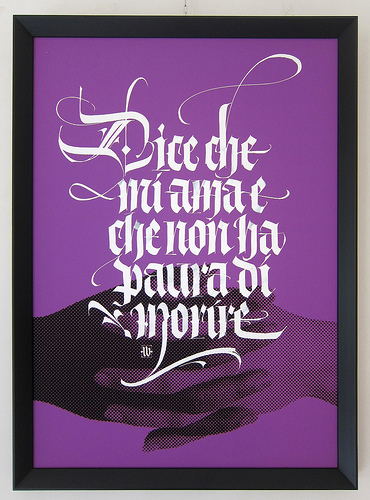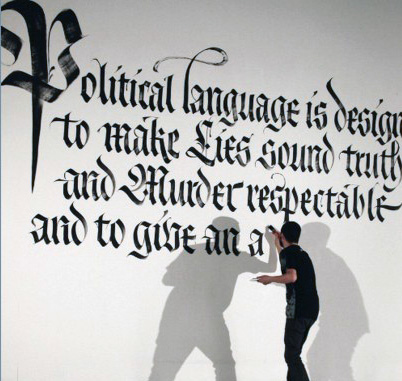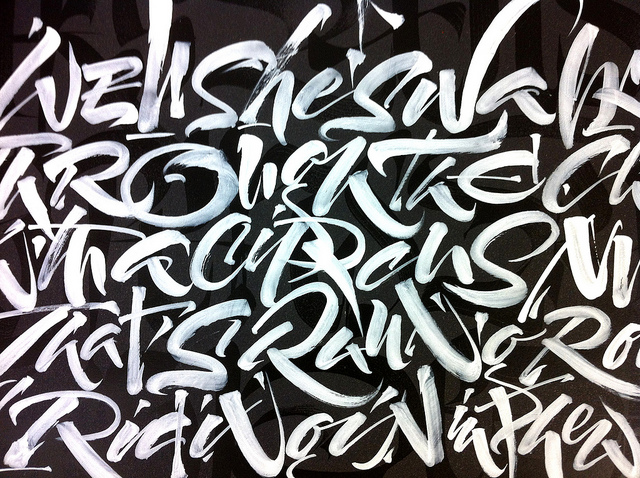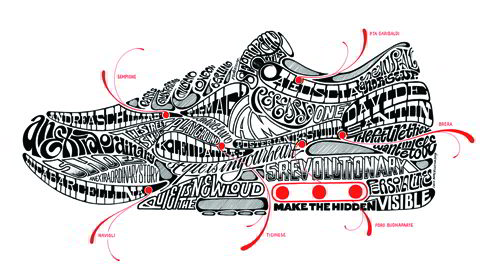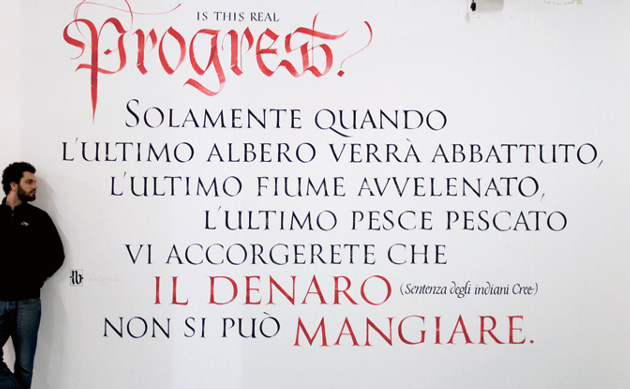
Luca Barcellona
Take Your Pleasure Seriously: calligraphy in contemporary graphic design
Luca Barcellona (1978) arbeitet als Graphic Designer und Kalligraf in Mailand und ist Mitglied der Associazione Calligrafica Italiana. Er rettet mit seiner manuellen Fertigkeit die Tradition der alten Schreibkunst ins digitale Zeitalter. Zu seinen Kunden gehören Firmen wie Carhartt, Nike, Sony, Volvo, Universal und Montblanc. 2009 realisierte er für das Landesmuseum Zürich ein Replikat eines grossen Globus aus dem Jahr 1569. Luca Barcellona ist Mitglied des Kollektivs Rebel Ink, welches Liveperformances in Kalligrafie, Schreiben und Illustration durchführt. Seine Arbeiten sind in diversen Ausstellungen weltweit zu sehen und wurden in verschiedenen Büchern publiziert. Kürzlich erschien seine erste Monografie „Take Your Pleasure Seriously“ bei Lazy Dog Press.